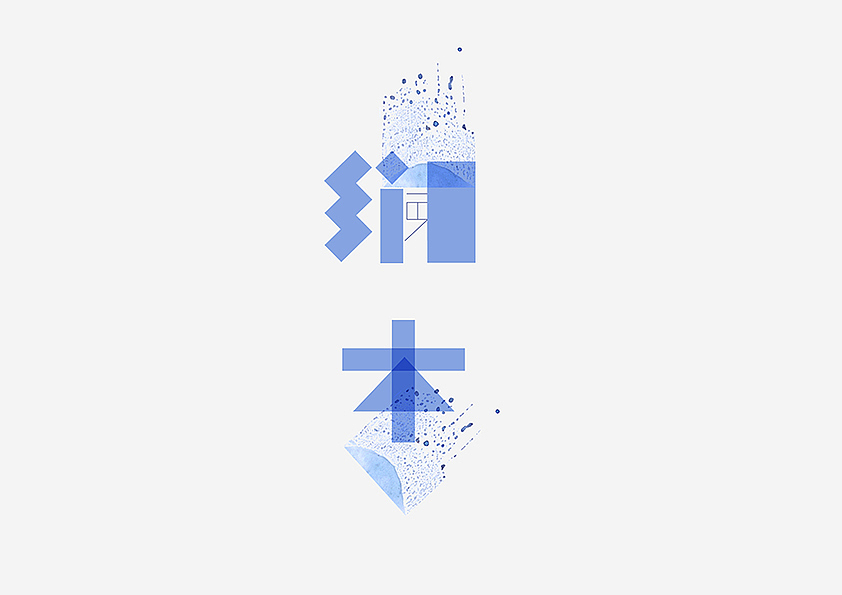
服装品牌“澜本“创意设计
服装品牌“澜本”创意设计及其创意说明
“澜本”即以水为本,该服装品牌主要产品是手工丝织品,所以希望我以水为主体展现出产品的柔和之美。
在汉字文化中,“氵”这个偏旁便是水的符号化表现,以此来表达品牌以水为本的概念再合适不过;尝试用不同的笔法去表现LOGO的形态
需要思考的第一个问题便是水和衣物的共通性开始进行头脑风暴,列出和水的特质相关的词汇,对比和服装的共同性,选出柔和的,流动的两个特质。概念一旦确定,便开始尝试不同的表现方式。
仿佛时间静止般,水的流动性和柔和质感跃然展现与纸上
服装品牌“澜本“创意设计
名片和信笺设计
信封和网页设计
我认为设计是没有失败的,落选的方案也是一种表现方式的探索,并不会因此而埋没,总会在将来的某一天绽放光芒。
不同的表现方法的尝试,墨水喷洒于纸上的效果,展现出水的生命力和自由性的特点。
然后进行与之搭配的字体设计